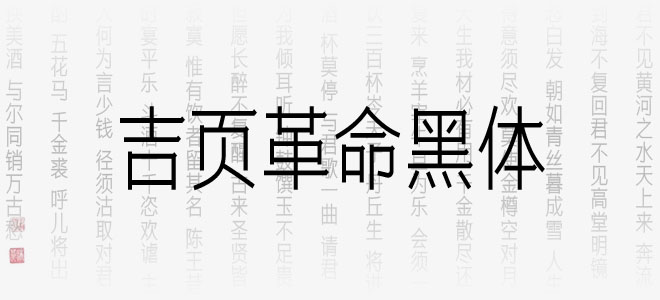
吉頁革命黑體字體是吉頁字庫推出的一款細(xì)黑風(fēng)格字體,該字體在等線筆畫的基礎(chǔ)上加入了襯線,字體軀體飽滿,更接近對稱,重心居上,更顯端莊,穩(wěn)重,儒雅之風(fēng),適應(yīng)于各種海報(bào)、 畫冊、書籍、影視、廣告、導(dǎo)視等領(lǐng)域使用,歡迎大家前來下載。